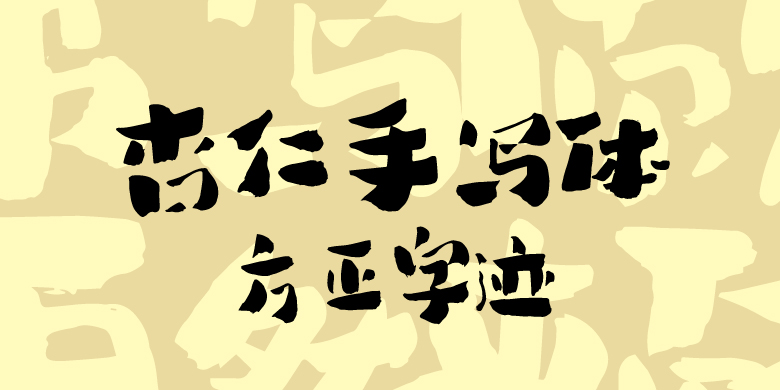
方正字迹-杏仁手写体
创意书写
方正字迹-杏仁手写,是一款既有孩童的活泼和趣味,又不失雅致和质朴的字体。字体取材日常随性手写笔触,摒弃规整印刷棱角,以生活化书写质感为核心,还原纸笔书写自然顿挫,打破标准字的刻板拘束,适配生活化、文创、童趣类场景,让文字自带手写温度。可应用于logo、海报、文创、标题等。